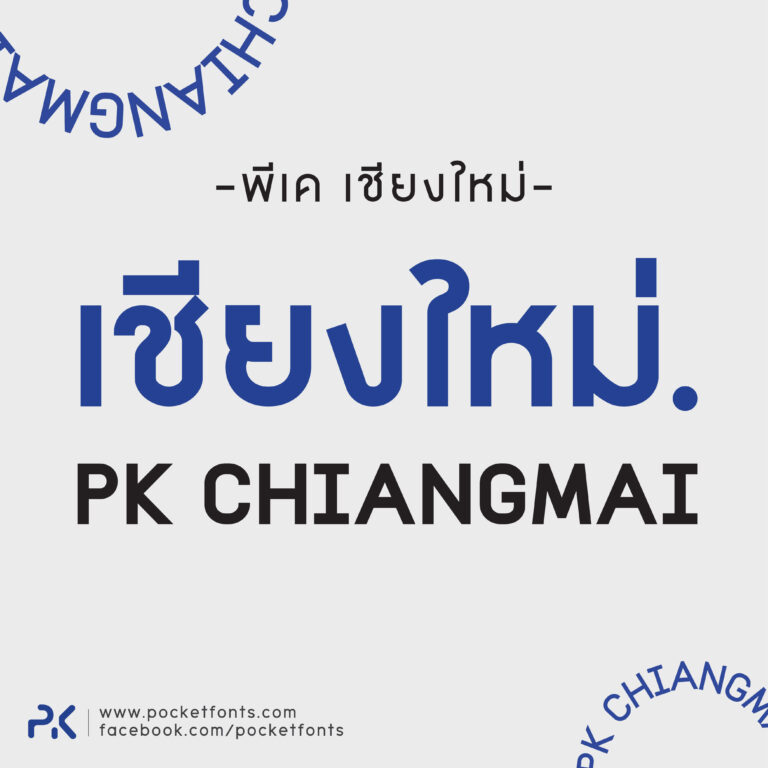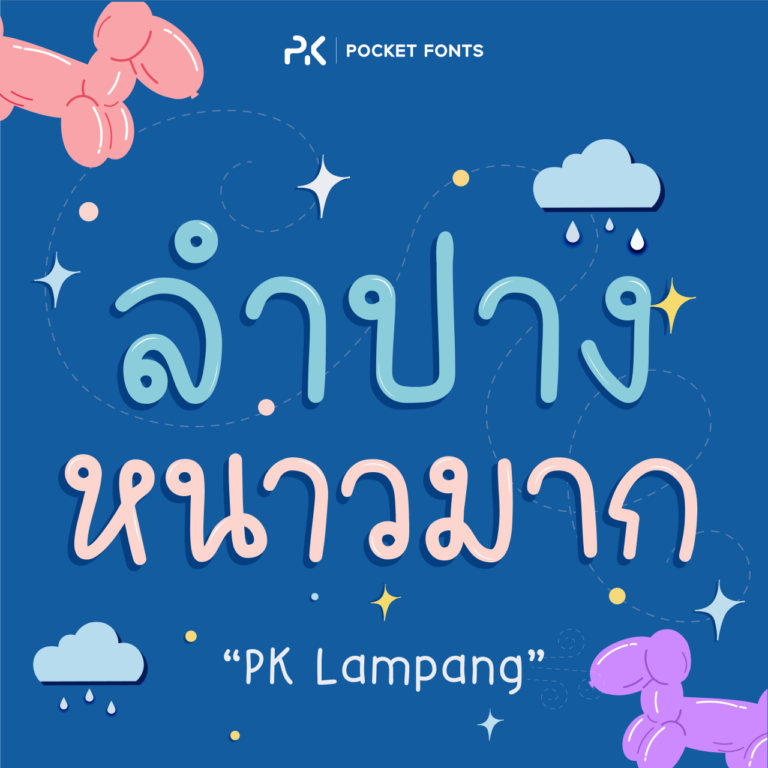
Pocket Fonts
สร้างสรรค์ฟอนต์ไว้ทั้งหมด 24 ตัว
พีเค กรุงเทพ | PK Krung Thep
ฟอนต์ พีเค กรุงเทพ (PK Krung Thep) เป็นฟอนต์สไตล์โมเดิร์น ดีไซน์โค้งมน ดูเรียบง่าย ทันสมัย สะอาดตา อ่านง่าย มีด้วยกัน 7 น้ำหนัก และเป็น Variable font สามารถปรับน้ำหนักแบบ Custom ได้
พีเค อ่างทอง | PK Ang Thong
ฟอนต์ พีเค อ่างทอง (PK Ang Thong) เป็นฟอนต์มีโครงสร้างส่วนใหญ่เป็นเรขาคณิต จุดปลายมุมจะมีความเป็นเหลี่ยมตัด ส่วนโค้งหรือหัวก็จะเป็นวงกลม โดยรวมดูแล้วให้ความมั่นคงแข็งแรง แต่ก็มีความไม่เป็นทางการเนื่องจากหัวค่อนข้างโตผิดปกติ 55
PK Sukhothai
ฟอนต์ PK Sukhothai ผสมผสานความโมเดิร์นทันสมัย แบบ Latin รวมกับความเป็นไทยด้วยปลายที่แหลมและเอียงไปด้านนึงคล้ายกับลักษณะการเขียนอักษรไทยแบบอาลักษณ์ ผสมผสานกันอย่างลงตัว
พีเค สมุทรสงคราม | PK Samut Songkhram
เริ่มจากการที่เป็นคนชอบจดและเขียนหนังสือมากๆ คนนึง ชอบจดเลกเชอร์ตอนเรียนรวมถึงจดโน้ตต่างๆในชีวิตประจำวัน มักใช้การเขียนมากกว่าการพิมพ์ พอถึงช่วงที่ยุคสมัยเปลี่ยนไป เรียนจบแล้วก็ไม่ค่อยได้ใช้ปากกาจดเท่าไหร่ จะกลายเป็นใช้การพิมพ์ทุกอย่างลงโน้ตและแพลนเนอร์ออนไลน์แทน เลยอยากจะมีฟอนต์ที่มีลายมือของตัวเอง จึงเกิดฟอนต์นี้ขึ้นมา
พีเค ภูเก็ต | PK Phuket
ฟอนต์นี้ทำขึ้นมาทั้งหมด 3 น้ำหนัก ตัวหนา ตัวธรรมดา และตัวบาง พร้อมทั้งตัวเอนของแต่ละน้ำหนัก สามารถดาวน์โหลดไปใช้ได้ฟรี 1 น้ำหนัก (ตัวธรรมดา)
พีเค แม่ฮ่องสอน | PK Maehongson
เป็นฟอนต์ตัวแรก(ที่ทำจนเสร็จ) ของผมเลยครับ พยายามทำให้ดูโมเดิร์นๆ เพราะส่วนตัวชอบใช้ฟอนต์แนวนี้ทำงานอยู่แล้วเลยคิดว่าถ้ามีเป็นของตัวเองบ้างก็คงจะดี แต่ด้วยความที่ยังเป็นมือใหม่เลยอาจจะยังมีข้อบกพร่องอะไรอยู่บ้าง ฝากแนะนำติชม หรือหากพบเจอปัญหาในการใช้งานรบกวนช่วยแจ้งเข้ามาได้เลยครับ.